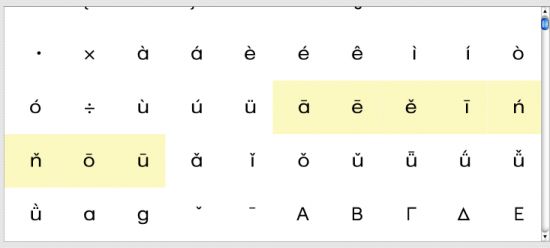
PINYIN-Diakritika - Erweiterter Zeichensatz
An alle Schriftgestalter und -modifizierer, und alle, die welche kennen :D, hätte ich eine Bitte bzw. Anregung:
Die mittlerweile allgemein gebräuchliche Umschrift fürs Chinesische ist Pinyin. Da kommt man ohne weiteres mit unserem Alphabet aus, einzig den Umlaut "ü" benötigt man zusätzlich. "Volksrepublik China" lässt sich beispielsweise so sehr schön als "Zhonghua Renmin Gongheguo" schreiben.
Allerdings gehören zum "richtigen" Pinyin auch die Tonzeichen, denn das Hochchinesische kennt vier Töne, die durch verschiedene Akzentzeichen kenntlich gemacht werden:
1. "ebener" Ton: ein gerader Strich über dem tragenden Vokal.
2. "ansteigender" Ton, ein Akzent ´
3. Ton. Der geht erst runter, dann rauf, entsprechend die Darstellung als umgekehrter Zirkonflex.
4. "fallender" Ton, Akzent `
Zweiter und vierter Ton sind natürlich kein Problem, auch für den ersten und dritten Ton finden sich manchmal Glyphen. Blöd wird's allerdings, wenn das ü tragender Vokal ist: Dann gehören die Akzente nämlich über die Pünktchen (Diaedingsbums).
Es wäre schön, wenn Zeichensätze diese Diakritika enthielten, so wie es chinesische Fonts in ihren lateinischen Abteilungen tun. Allerdings lässt da die Fotqualität arg zu wünschen übrig, und man braucht die Diakritika ja auch im "westlichen" Satz.
Hier mal ein Beispiel wie und wo (Latin Extended A und B) diese Zeichen eingelagert werden könnten (so machen es die Chinesen):
Oder kennt Ihr einen Zeichensatz, der so gut ausgebaut ist, dass man richtiges Pinyin schreiben kann?
... ich weiß. Ich hab in HH studiert, um die Zeit fingen die in Poppenbüttel gerade an, die ersten chin. Zeichen zu digitalisieren.
Mir geht's eigtl. mehr um die Diakritika in lateinischen Fonts, ich bin z.B. ebenin einem anderen Thread der Spur der Leitura gefolgt, die ist extrem gut ausgebaut - bis auf Pinyin. Was ich nicht verstehe, denn wer irgendwelche altgriechischen Kringel (oder ein Lang-s) in seinen Zeichensatz einbaut, sollte doch auch die Sprache der Milliarde berücksichtigen, oder?
Ja, ich werde wohl mal eine Schrift zu meiner Lieblingsschrift für Chinesisch-Propjekte erklären müssen und dann beim Hersteller meiner Wahl nachfragen, ob er mir was einbaut. Fürs Rumbasteln mit Fontographer und Co. bin ich leider zu ahnungslos.
Die Lernbücher, die korrektes Pinyin verwenden, sind meist aber sehr langweilig gesetzt ...
>Die Lernbücher, die korrektes Pinyin verwenden, sind meist aber sehr langweilig gesetzt ...
Dieses sicherlich.
Hallo! Ja, Pinyin ist interessant. Es ist in jedem chinesischen Font integriert und für uns Laowai in der Glyphentabelle zu finden, es gibt aber auch fürs Internet eine Kodierung "pinyin", entsprechende Kodes gibt es auf der Seite http://www.pinyin.info zu sehen - hier kann man auch einige Hintergrundinformation zum Thema Romanisierung erhalten. Bei Hanyu Pinyin wird das kursive a bzw. g (bzw. "Futura-a") verwendet.
Leider ist dem Pinyin eine ähnliche Rolle wie die der Gebärdenschrift beschieden: Sie dient nur der Lehre, später wird sie nur noch selten benutzt.
Und bei vielen Lehrbuchverlagen in China selbst hat es ästhetisch einen Rückschritt gegeben. In den 1990er-Jahren ist der Glaube aufgekommen, man müsse für Pīnyīn unbedingt ein »geschlossenes« ɑ und ɡ mit rechts angesetzter, offener Unterlänge (statt »offenem« a und g mit geschlossener Unterlänge) verwenden, und am besten eine Grotesk. Chinesische Typografen haben dafür Schriften geschaffen, die von erstaunlicher Unkenntnis lateinischer Typografie und von einem erstaunlichen Mangel an Sinn für Proportionen zeugen. (Zu bewundern ist das z.B. in dem sehr verbreiteten Lehrwerk New Practical Chinese Reader / Xīn shíyòng Hànyǔ kèběn 《新实用汉语课本》).
dieses elektronische Schreiben
Ein weiterer Effekt der neuen Art zu schreiben: Viele eigentlich gebildete junge Leute beherrschen erschreckend viele Zeichen (außerhalb der ca. 2000 gebräuchlichsten) nur noch passiv, d. h. sie können sie nicht »auswendig« schreiben.
Adobe hat Minion ausgebaut, der 2018 veröffentlichte Zeichensatz heißt jetzt Minion 3 und unterstützt unter anderem Pīnyīn (und IPA).